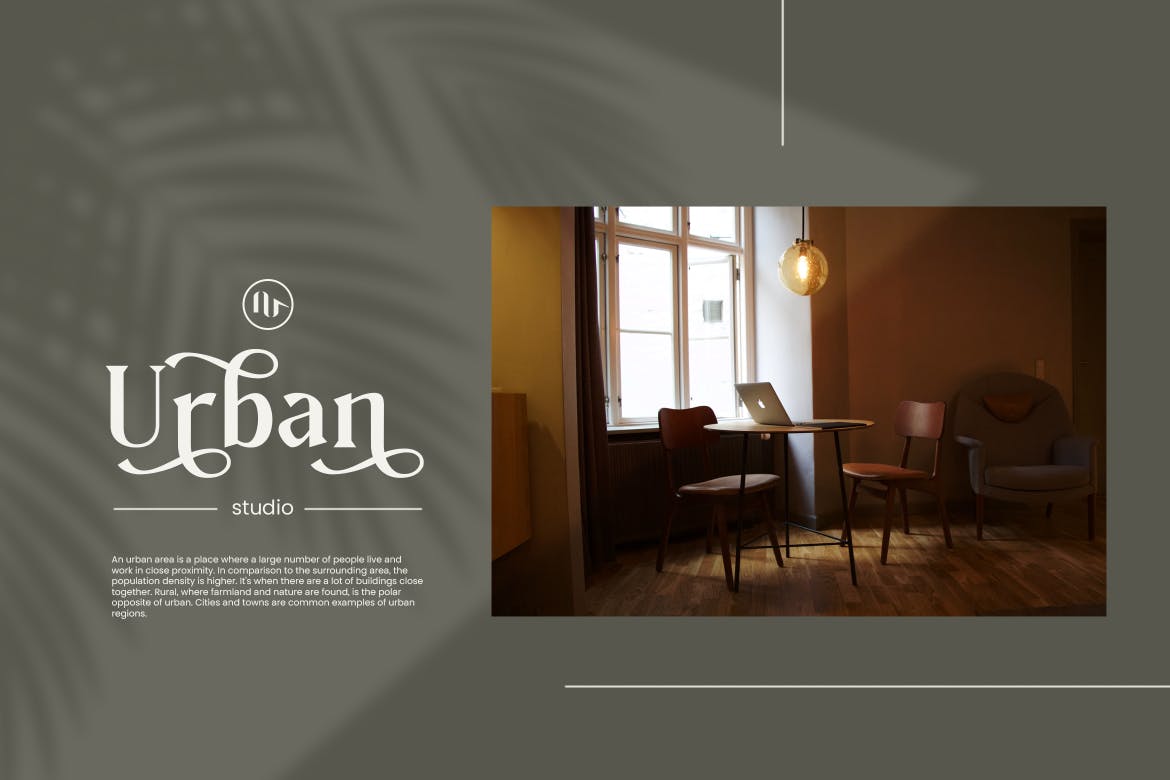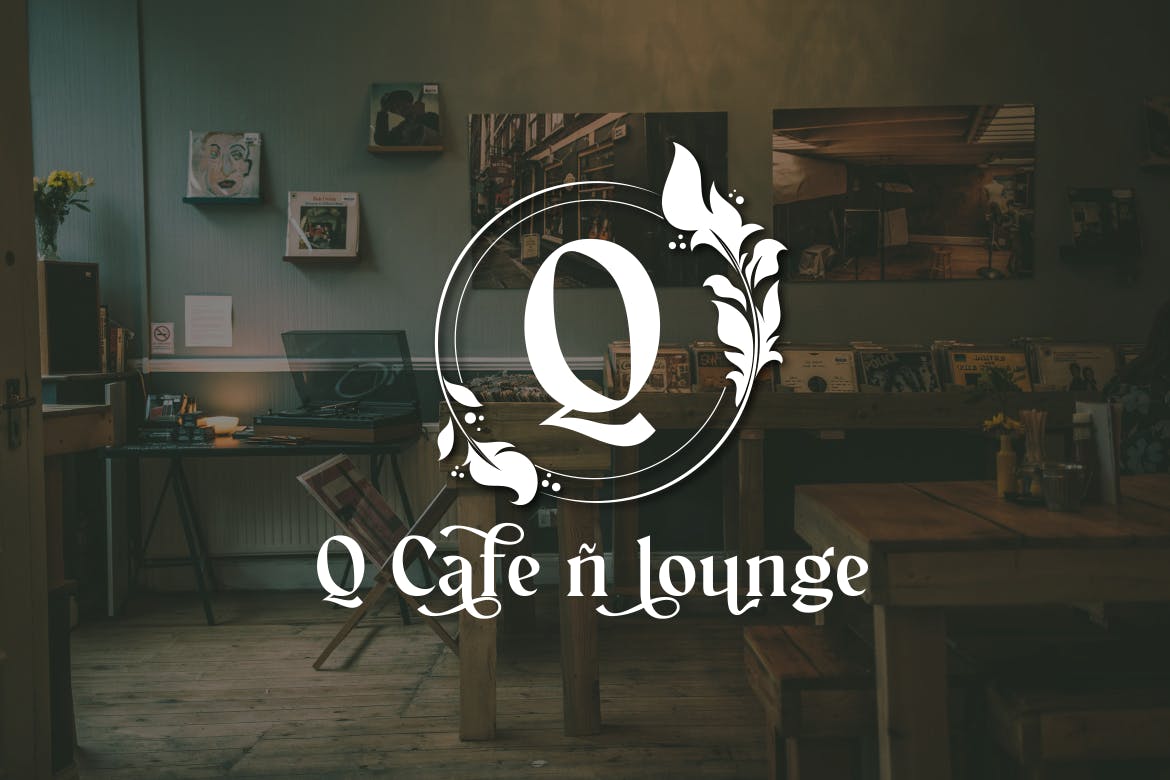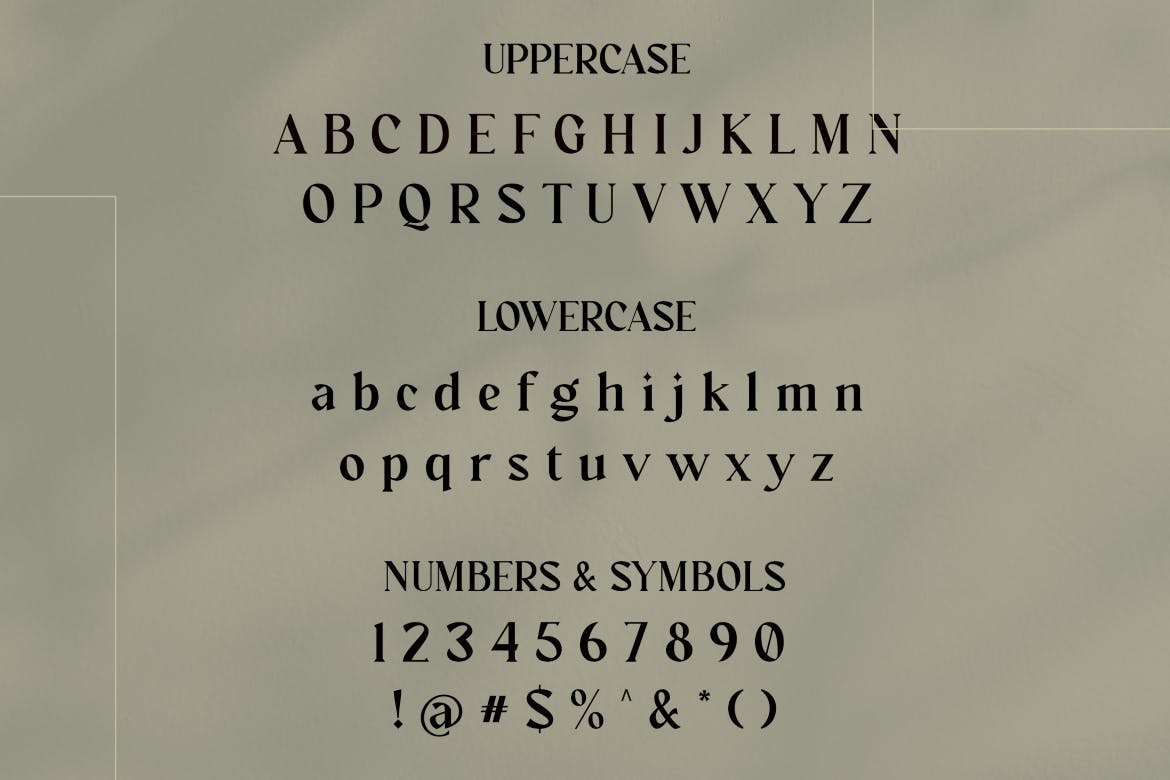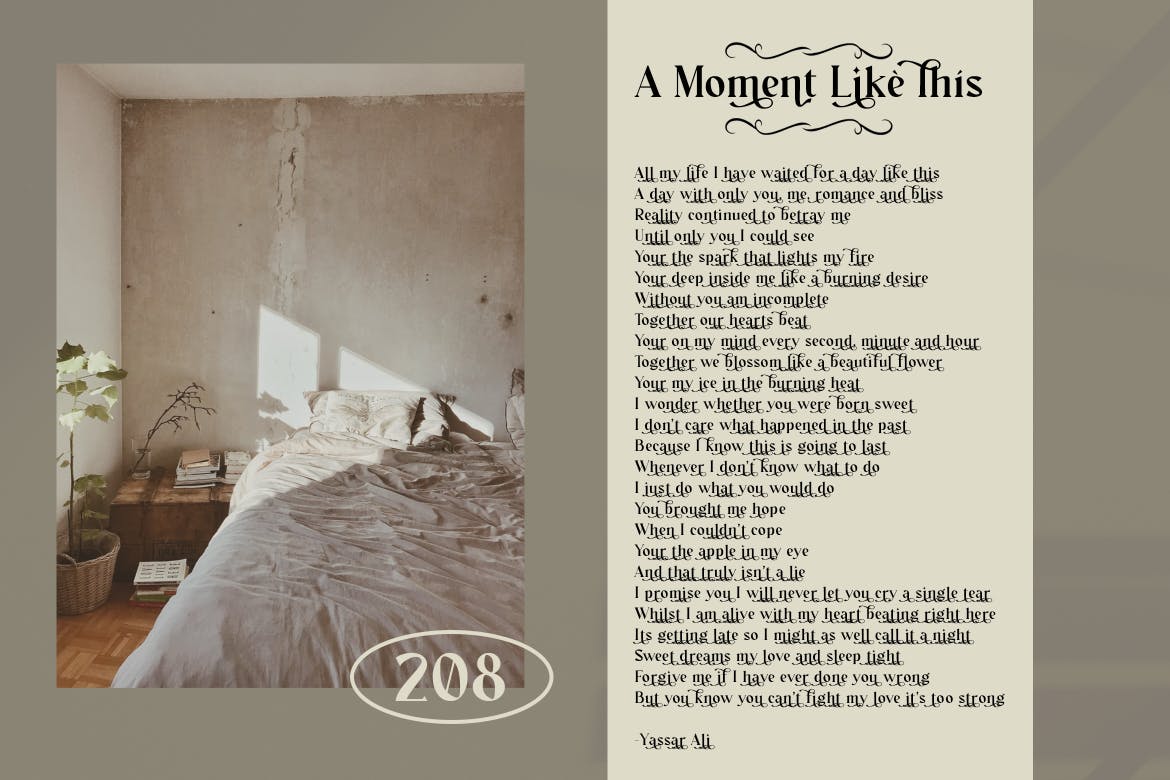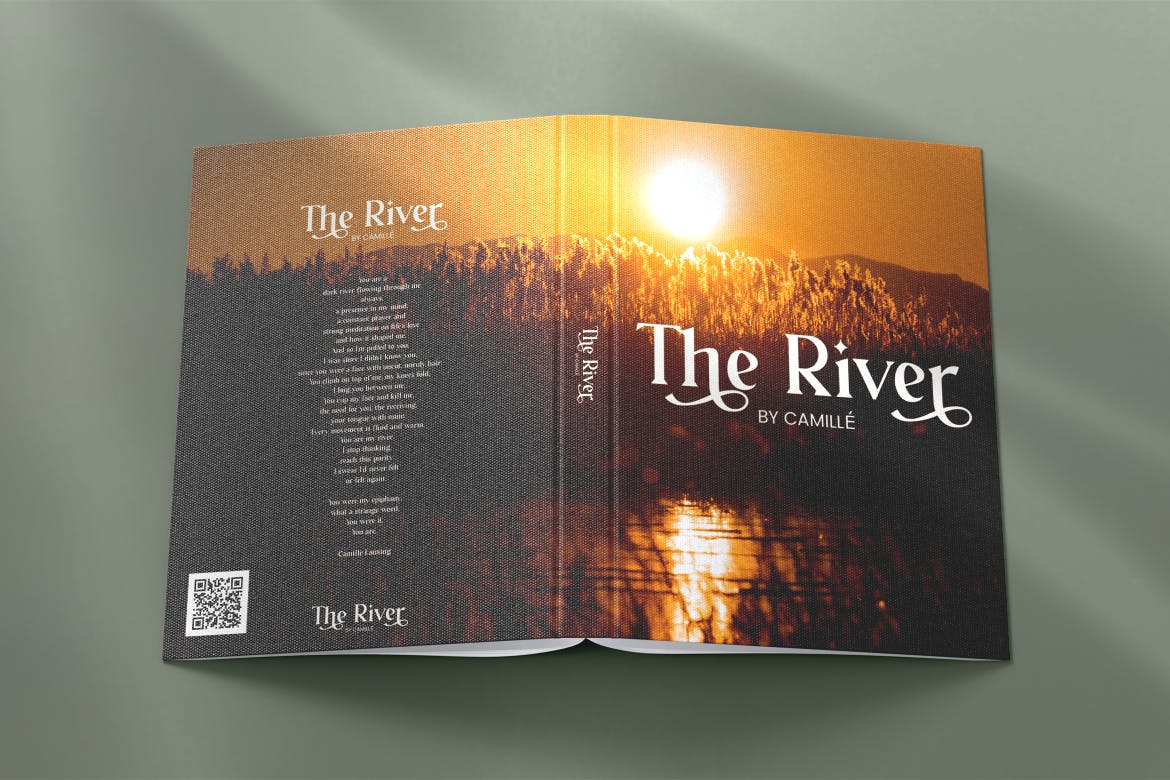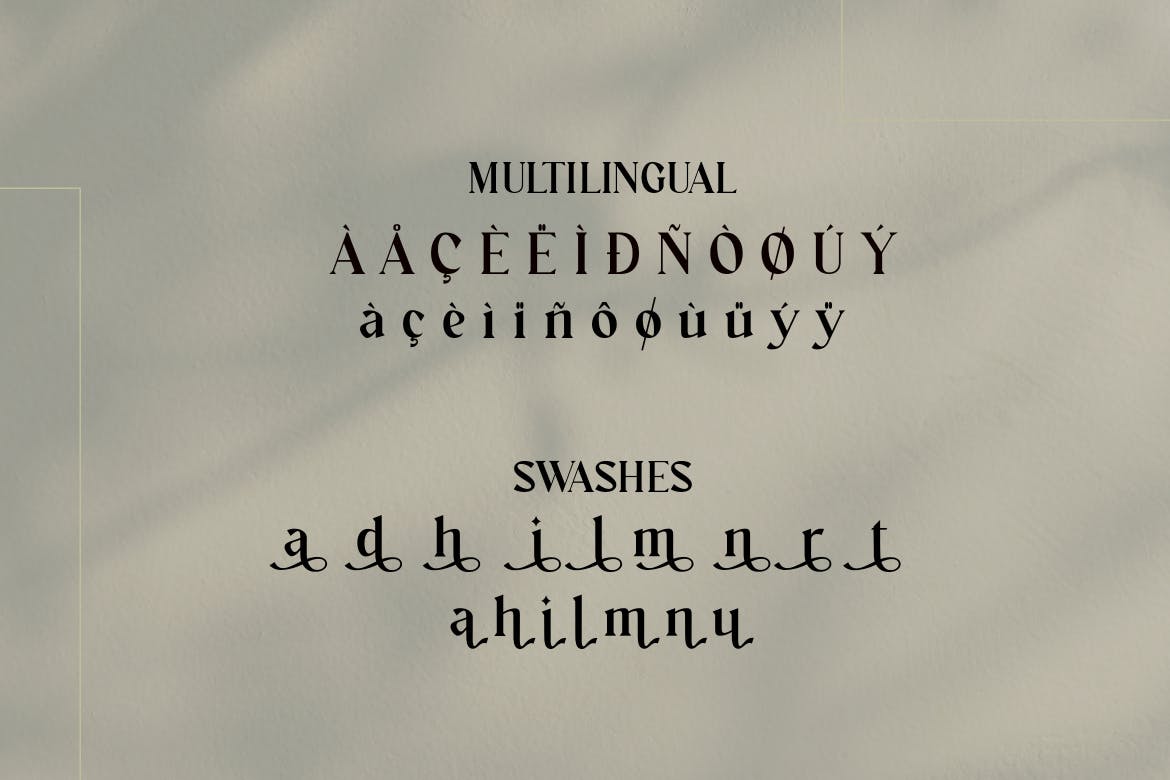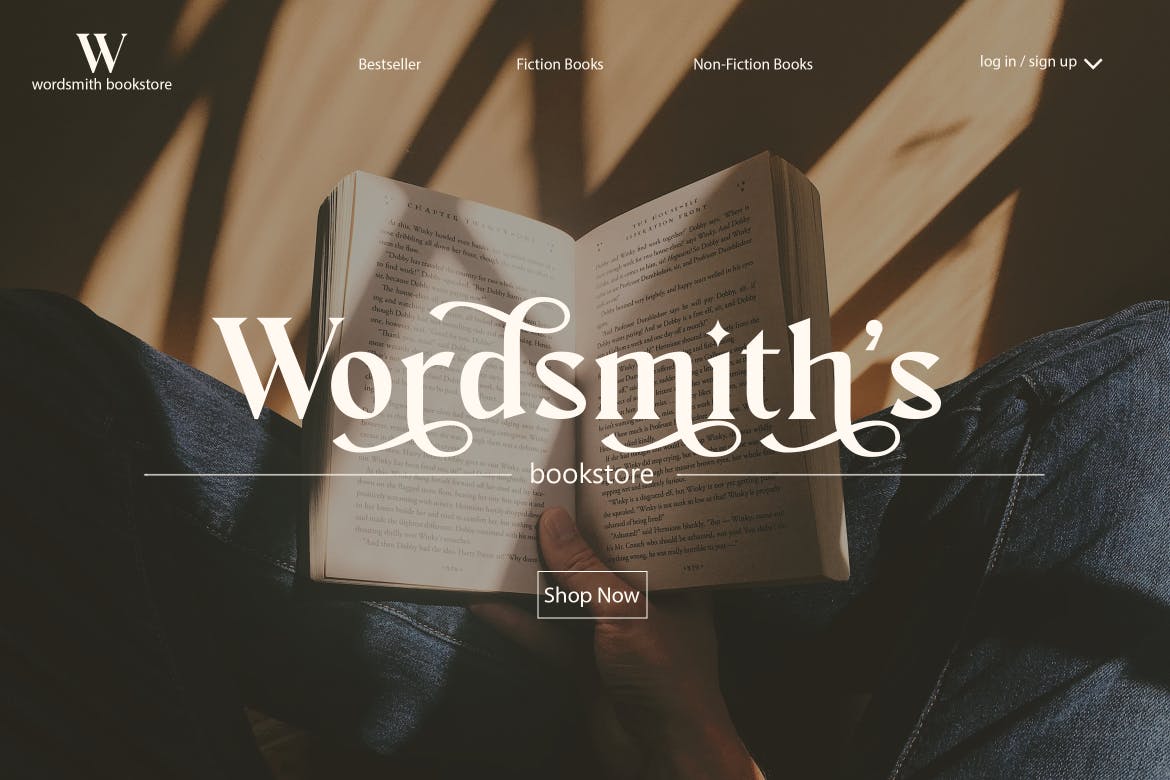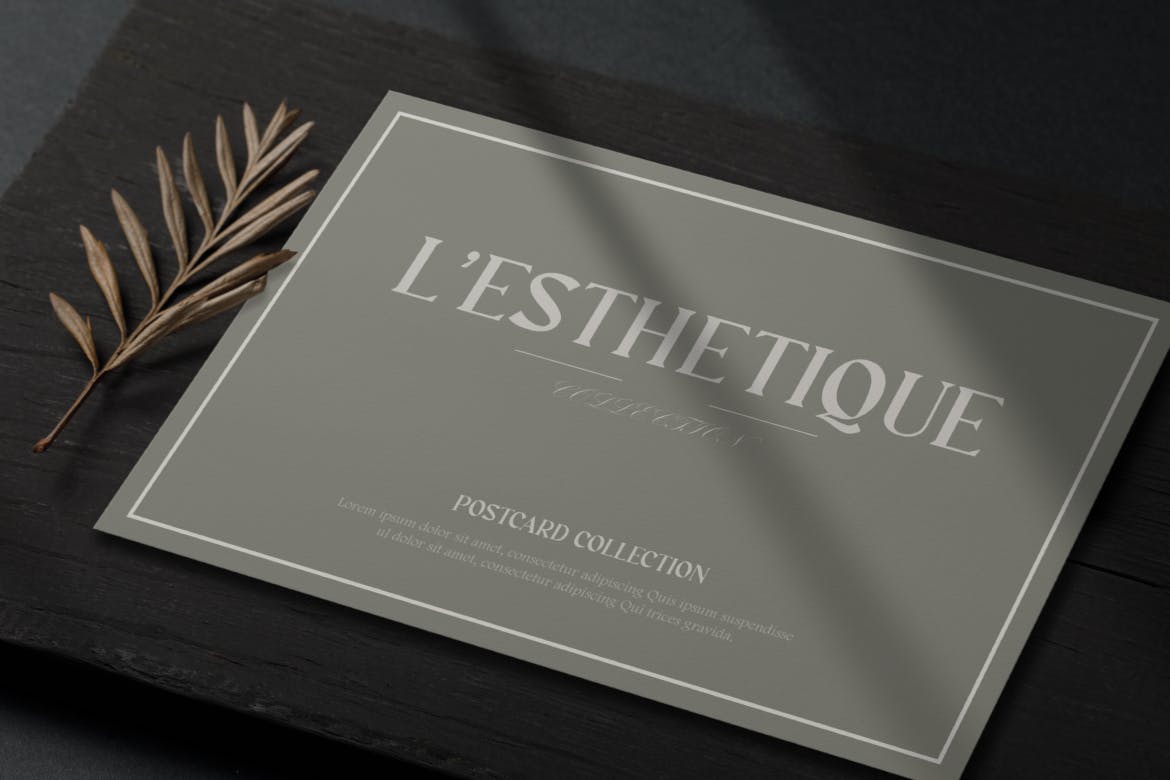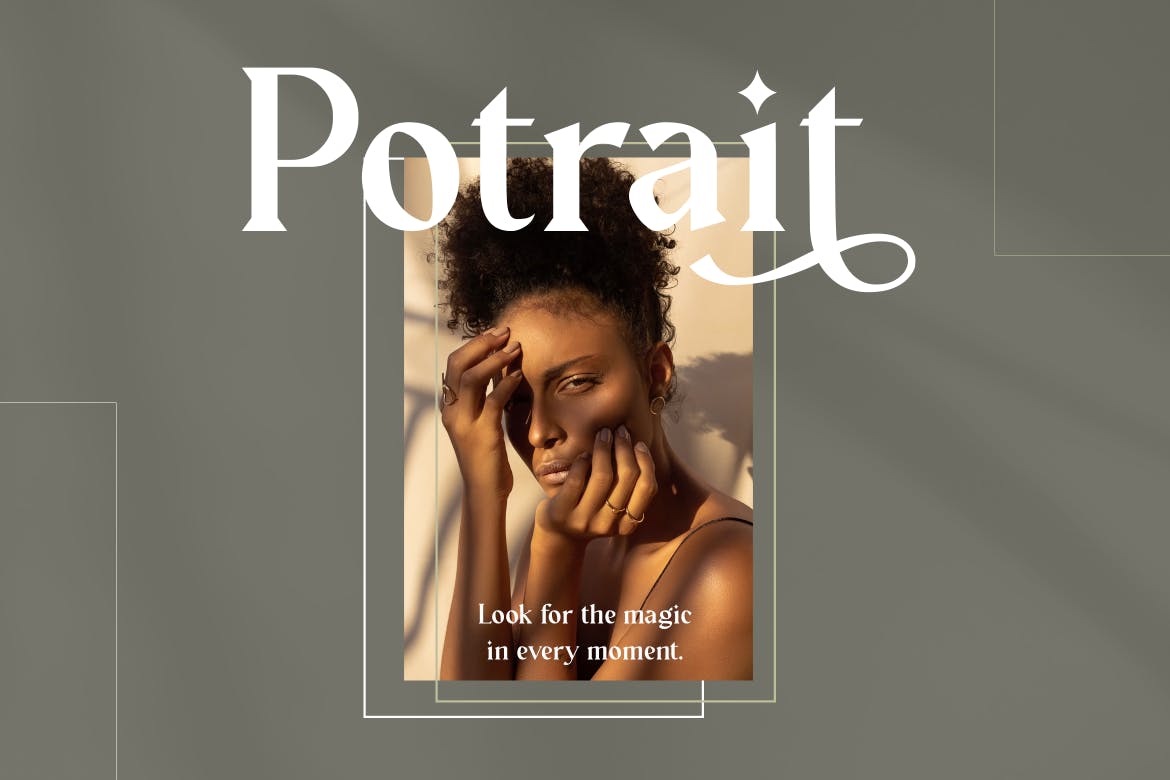
معرفی میکنیم Vergian – یک فونت مدرن با طراحی سریف.
این فونت تمیز و قابل خواندن، انتخابی مناسب برای هر متنی است که نیاز به برجسته شدن دارد. امتحان کنید و تفاوت یک فونت عالی را ببینید.